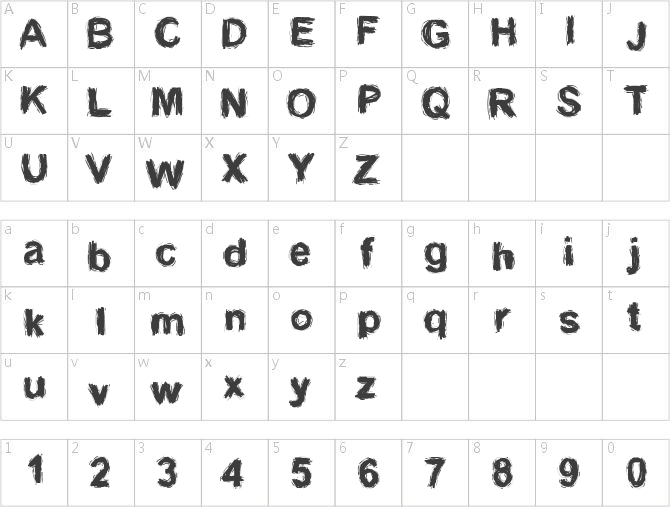
SplinterWood
SplinterWood介紹
SplinterWood字體字庫(kù)是一款讓人賞心悅目、百看不厭的英文字體,適合各類廣告和產(chǎn)品包裝設(shè)計(jì)應(yīng)用,字體大小0.12MB,格式為ttf字體,上傳用戶是細(xì)雪無(wú)聲,作者/版權(quán)方為未知